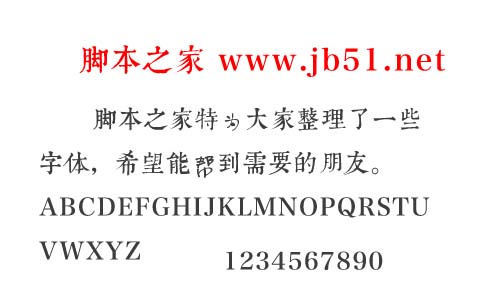
康煕字典體是一款基于道光版《康熙字典》原本開發(fā)的古樸風格的字體,其字體古樸蒼勁,屬于古典印刷體,包含了康熙字典體的簡體與繁體,可以用于日常文檔編輯,比較適用于古體書籍版式及表現(xiàn)古典風格包裝的設計,也能夠用于海報、廣告等設計領域,歡迎有喜歡或需要此字體的朋友們前來下載使用。
康熙字典體特色介紹:
1、筆鋒犀利,熱情奔放,美觀大方5、
2、適用于廣告設計、平面設計、標題正文、書法繪畫等領域
3、總共收錄47037個繁體漢字
4、最具古典風格的繁體字
5、無論在筆鋒、風格都十分具有特色